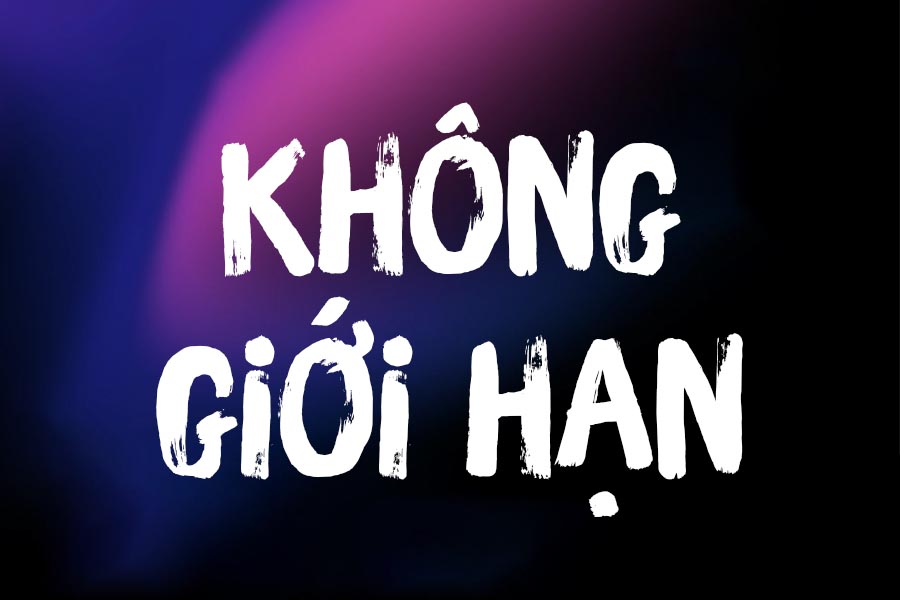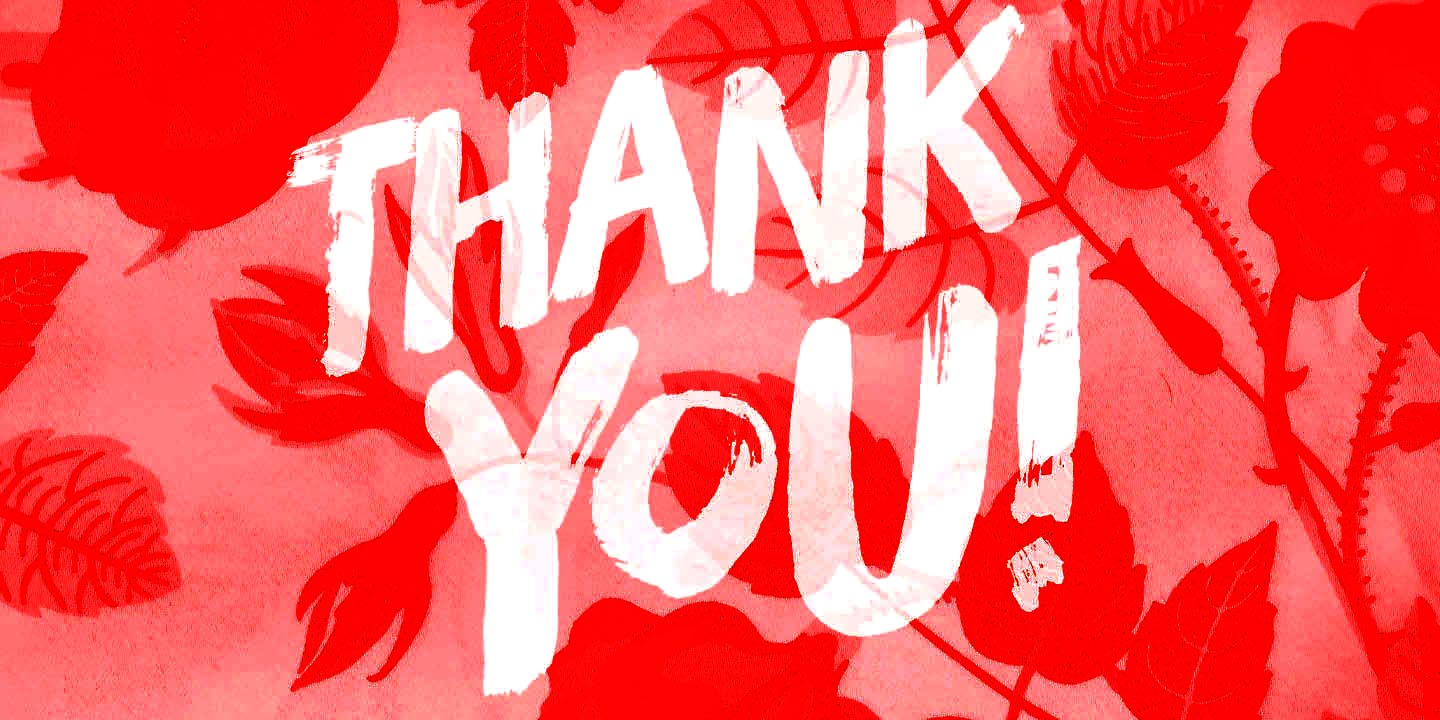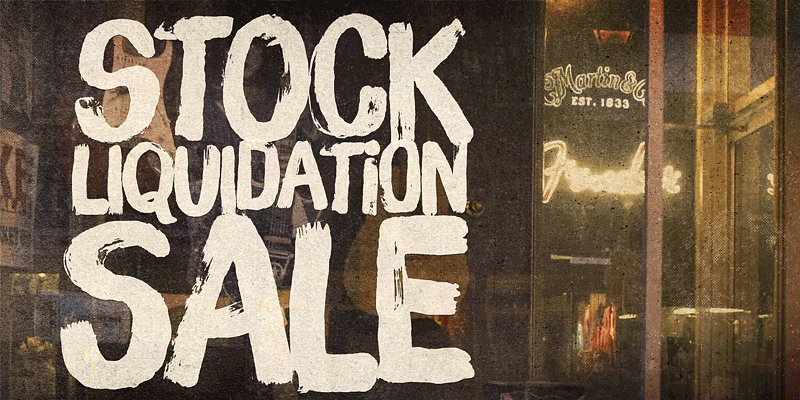
Trong thế giới thiết kế hiện đại, font iCiel Brush Up được xem là một trong những lựa chọn độc đáo dành cho những nhà sáng tạo yêu thích sự tự do và cảm xúc mạnh mẽ trong từng đường nét. Đây là phiên bản Việt hóa từ font gốc Brush Up của PintassilgoPrints, được đội ngũ iCiel thực hiện tỉ mỉ, mang lại trải nghiệm trọn vẹn cho người dùng Việt.
Điểm nổi bật của iCiel Brush Up nằm ở những nét chữ mô phỏng bút cọ chân thực. Các ký tự có độ dày mỏng không đều, tạo cảm giác như được vẽ bằng tay một cách ngẫu hứng. Chính điều này giúp font chữ trở nên sống động, mang hơi thở tự nhiên và khác biệt hoàn toàn so với những font chữ thẳng hàng, gọn gàng thường thấy.
Với ưu thế hỗ trợ đầy đủ bộ dấu tiếng Việt, font chữ nét cọ iCiel Brush Up dễ dàng ứng dụng trong nhiều dự án thiết kế: từ poster sự kiện, bìa sách, tạp chí, cho đến logo thương hiệu cá tính hay các ấn phẩm truyền thông đậm chất nghệ thuật. Đặc biệt, những thiết kế cần truyền tải cảm xúc mạnh, phong cách tự do hoặc tạo ấn tượng thị giác ngay lập tức đều phù hợp với font chữ này.
Không chỉ mang đến sự phóng khoáng, iCiel Brush Up còn gợi lên tinh thần sáng tạo và cá tính riêng cho từng sản phẩm thiết kế. Đây chính là lý do font chữ này ngày càng được nhiều designer trẻ ưa chuộng và nằm trong bộ sưu tập không thể thiếu của các nhà thiết kế chuyên nghiệp.